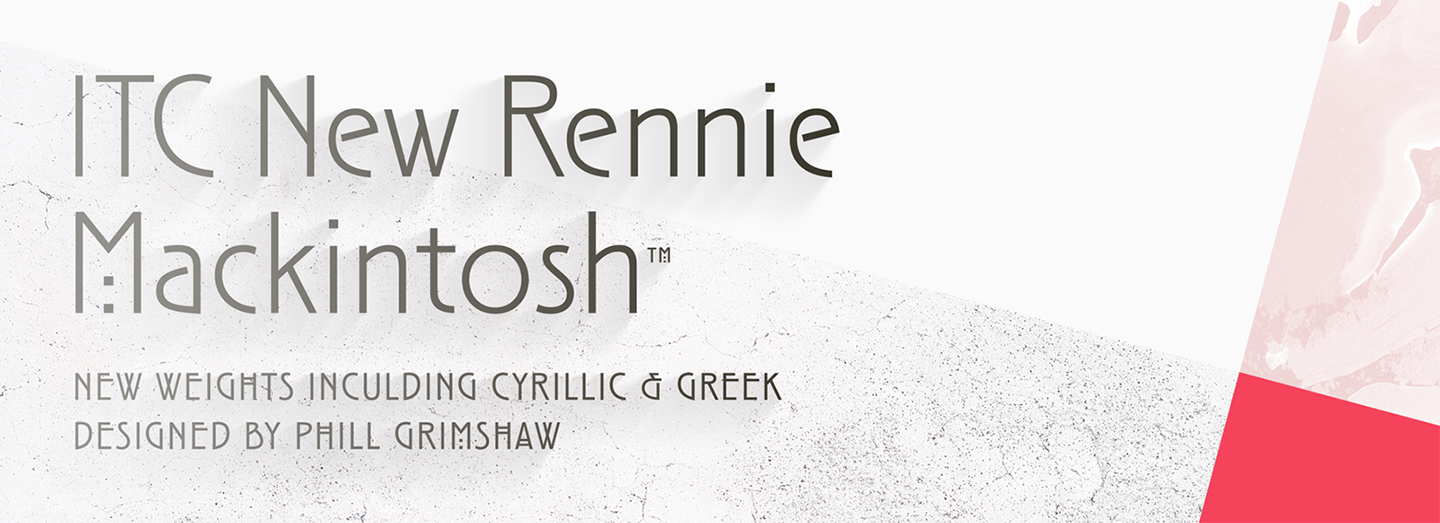
ITC New Rennie Mackintosh™
ITC New Rennie Mackintosh™,这款字体结构工整、笔画清晰,兼顾美观与易读性,适用于标题、正文、海报、包装、LOGO 等多种场景。字形优雅稳定,风格百搭耐看,适配日常排版与创意设计,让文字呈现更舒适、更具质感。ITC New Rennie Mackintosh™一笔一画,皆是细节,以均衡的比例、流畅的线条打造舒适视觉体验,字形端正大气,风格简约现代。无论是商业设计、品牌宣传还是日常排版,都能轻松驾驭,让文字更有格调与力量。ITC New Rennie Mackintosh™字体下载。
字体品牌: ITC(Monotype) 设计师:Monotype Design Studio; Grimshaw,Phill 字体分类:衬线体 字体属性:外文 字符集:Unicode 发布时间: 2018